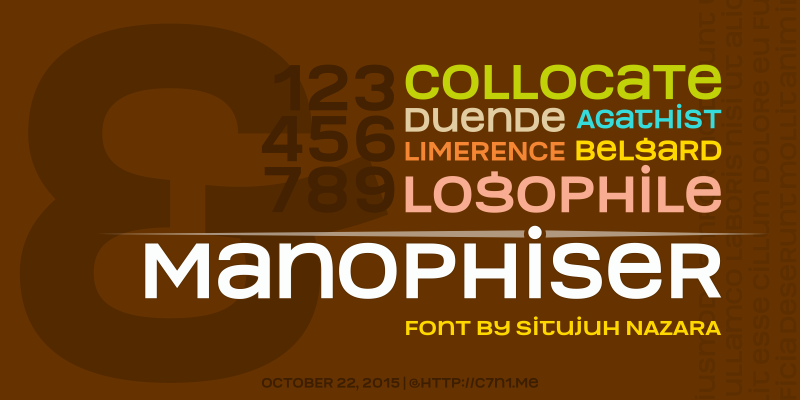
A Manophiser Font é uma sans-serif que oferece elegância contemporânea para seu design, combinando linhas suaves com uma aparência minimalista e limpa. Desenvolvida pelo designer Hamilton, essa fonte é perfeita para aplicativos digitais modernos, sites, ou qualquer outro projeto onde você quer manter um visual clean e acessível. Suas formas simples e eficientes permitem que você destaque o texto sem sobrecarregar seu design com complexidades superfluas. Ideal tanto para textos gerais quanto para headlines, ela é uma opção versátil que garante clareza e legibilidade em qualquer situação. Mesmo se você não estiver ciente da sua existência até agora, pode ser um acréscimo valioso a seu portfólio de recursos gráficos.